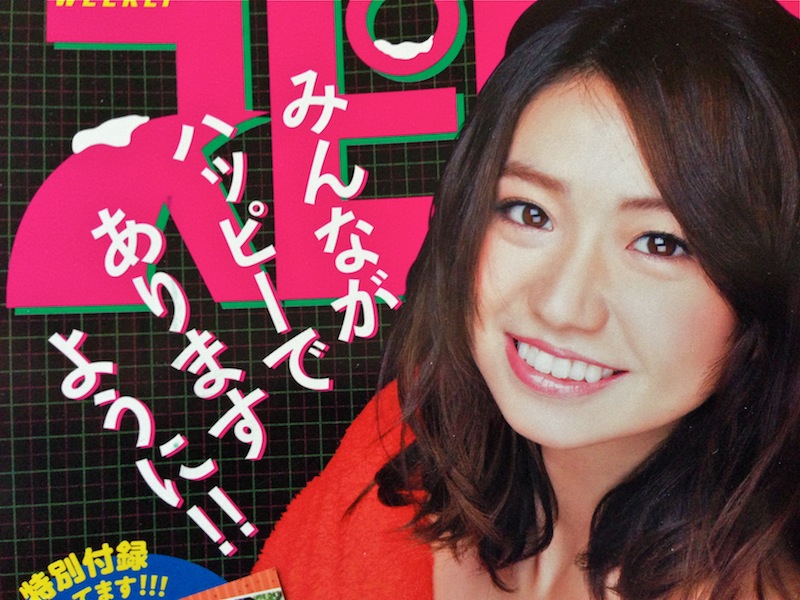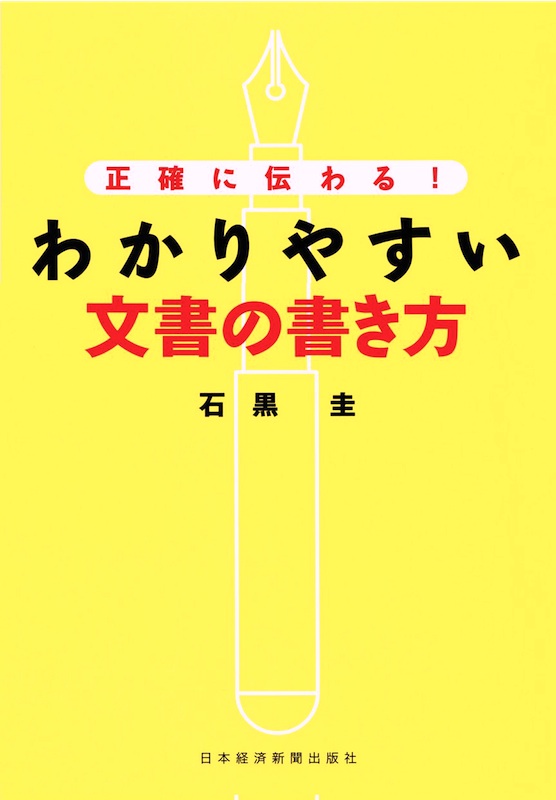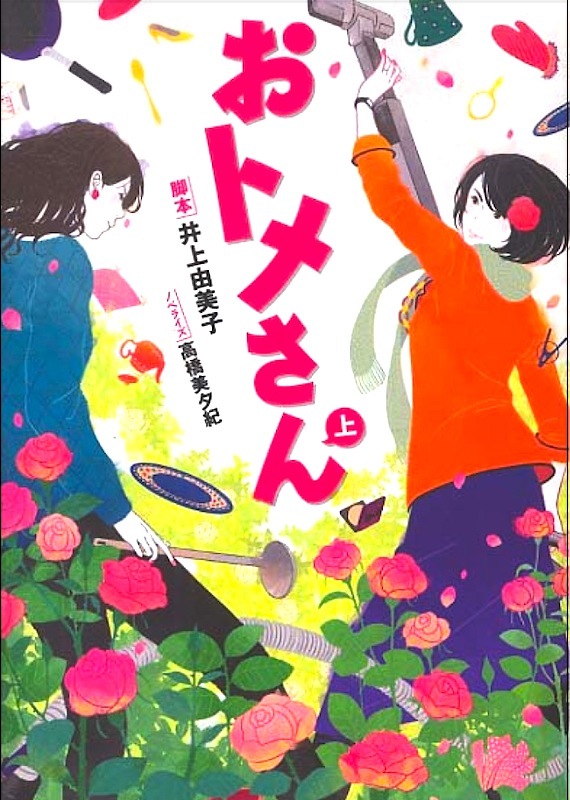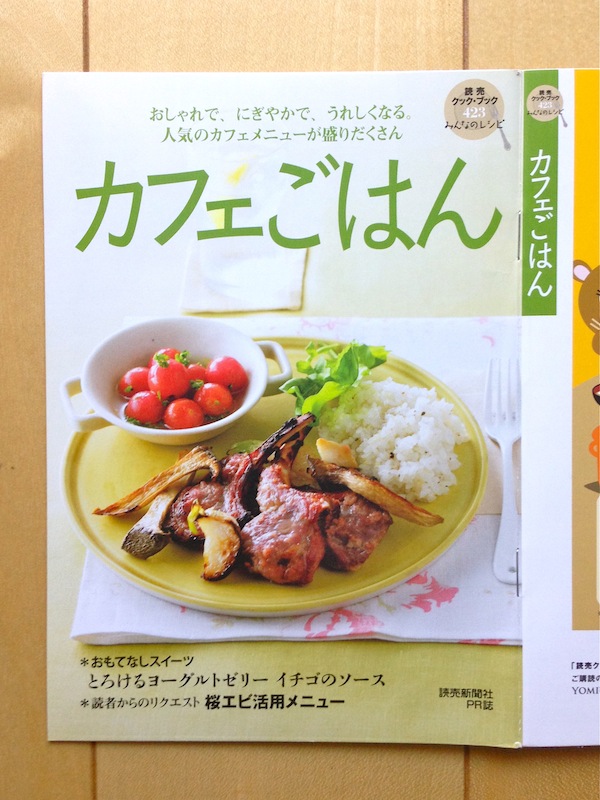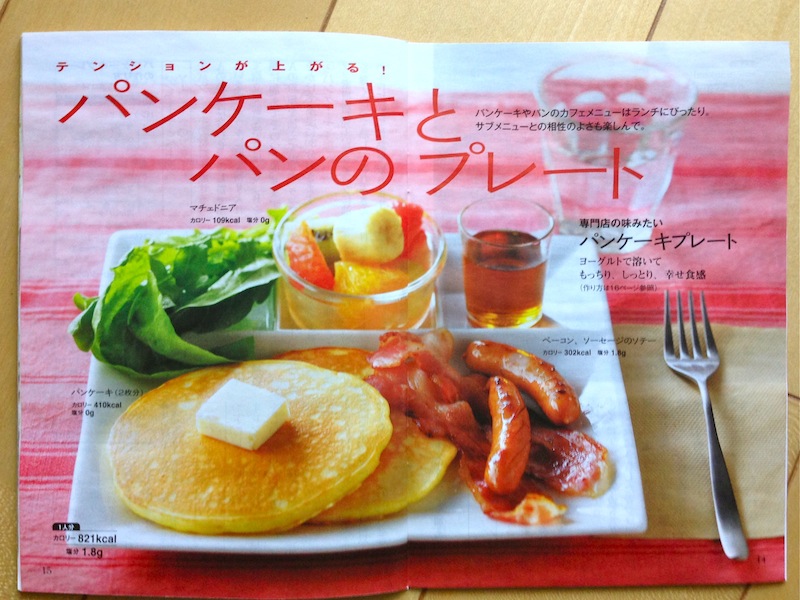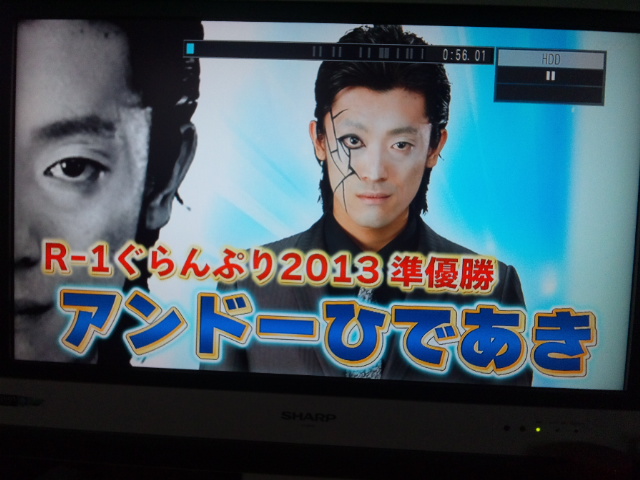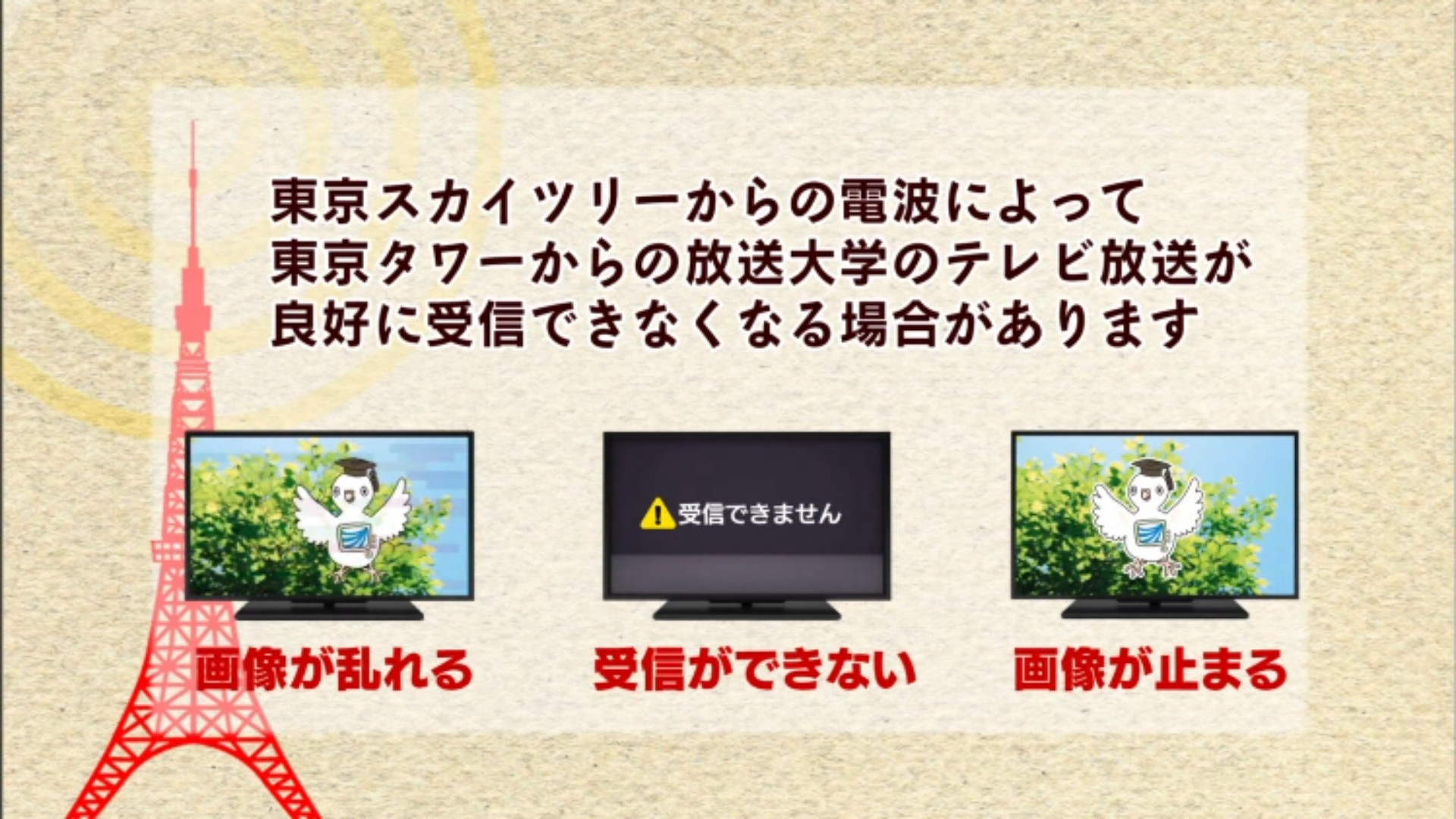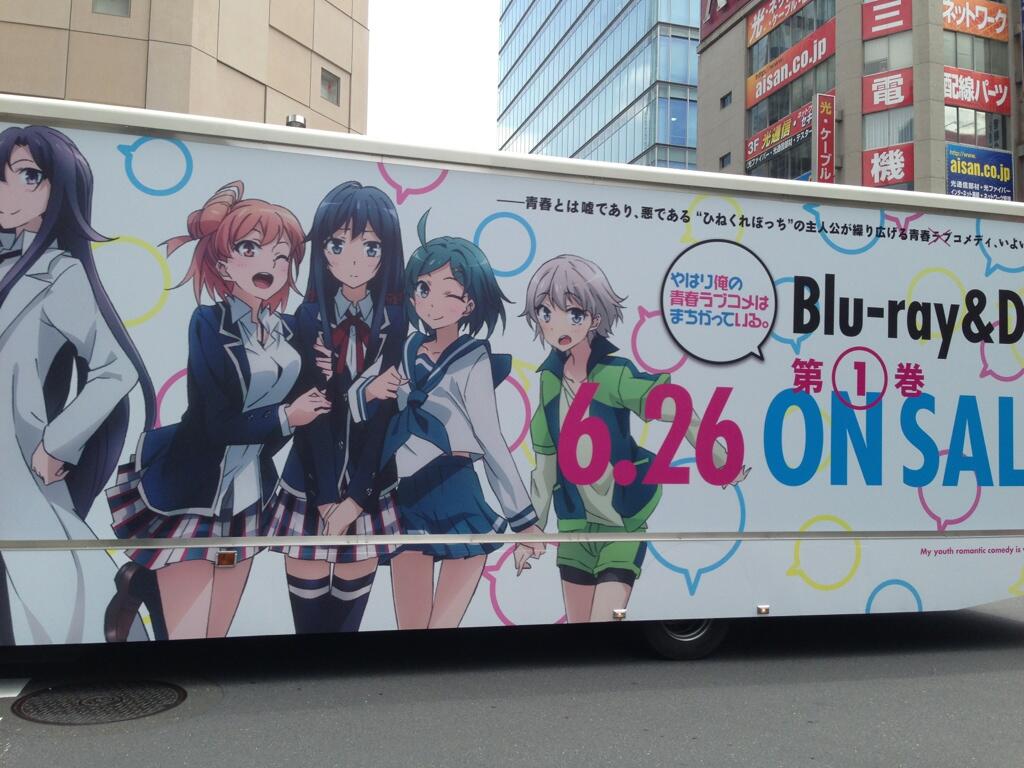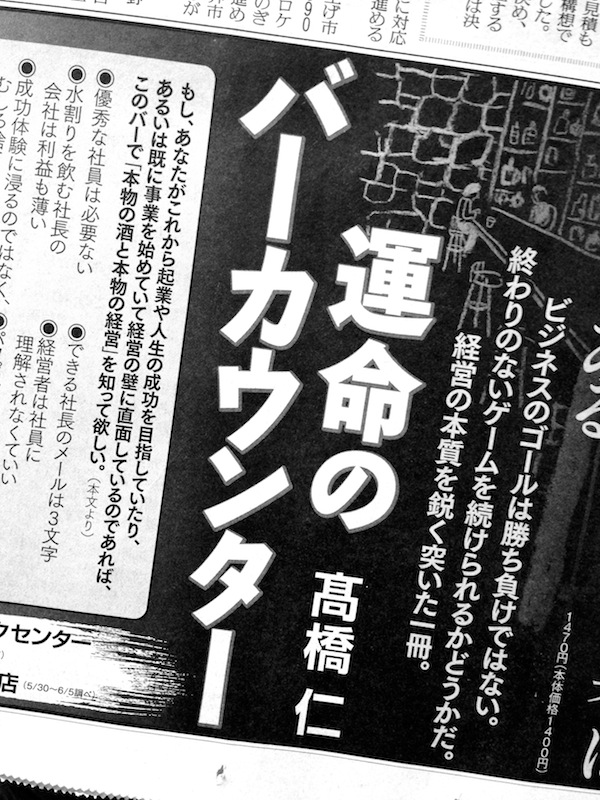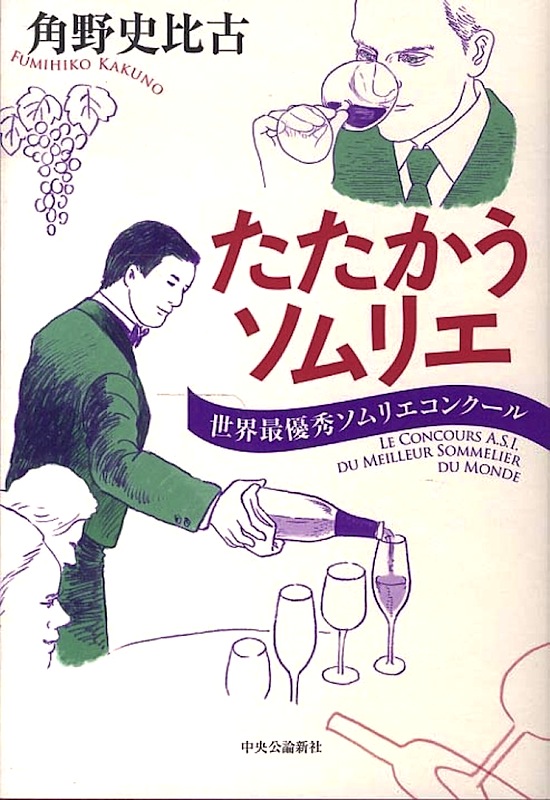
書名:ありがとう。バディ
著者:吉田太郎
発行:セブン&アイ出版
先日旅行で四国に行った時…。
書名:このミステリーがすごい!(2015年版)
著者:『このミステリーがすごい!』編集部
発行:宝島社
小さく、控えめに、細めの墨東。
書名:きらら
発行:小学館
PlayStation Vitaのゲーム『ガールズ&パンツァー 戦車道、極めます!』の公式サイトで墨東ルイカが使われています。
左下の桃色の「タイトル名」「プレイ人数」などが書かれた小さな文字です。
右下のコピーライト表記もルイカの英数字ですね。
お〜〜、こんな小さな場所…。よく気づいてくれました(笑)。
書名:くしカツさんちはまんいんです
著者:岡田よしたか
発行:PHP研究所
書名:さんすうサウルス
著者:ミッシェル・マーケル 絵:ダグ・クシュマン
翻訳:はいじま かり
発行:福音館
書名:そうちゃんはおこってるんだもん
著者:筒井頼子 文 / 渡辺洋二 絵
発行:福音館書店